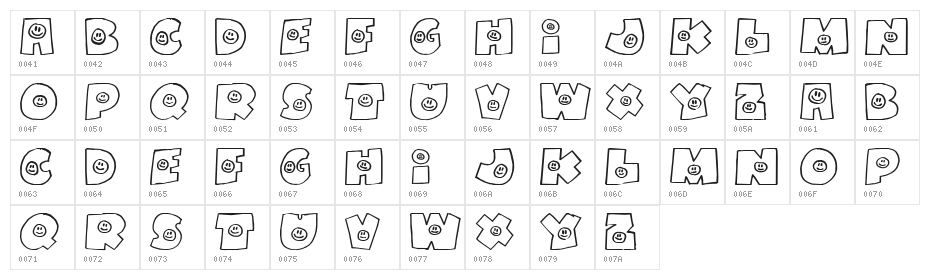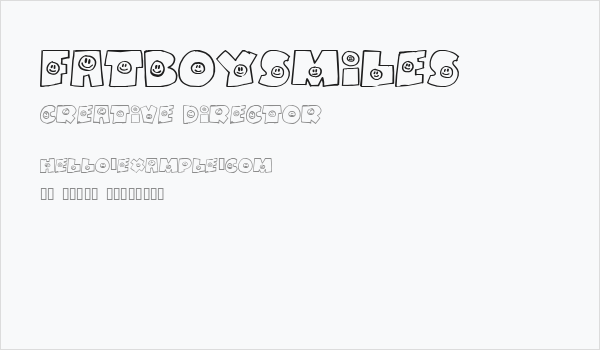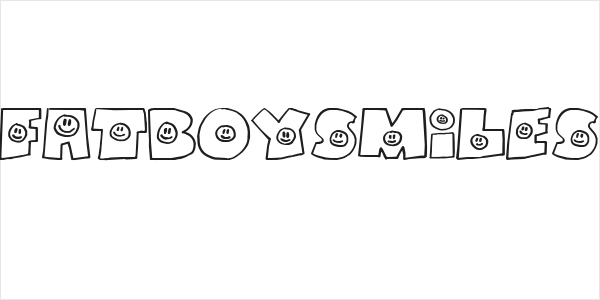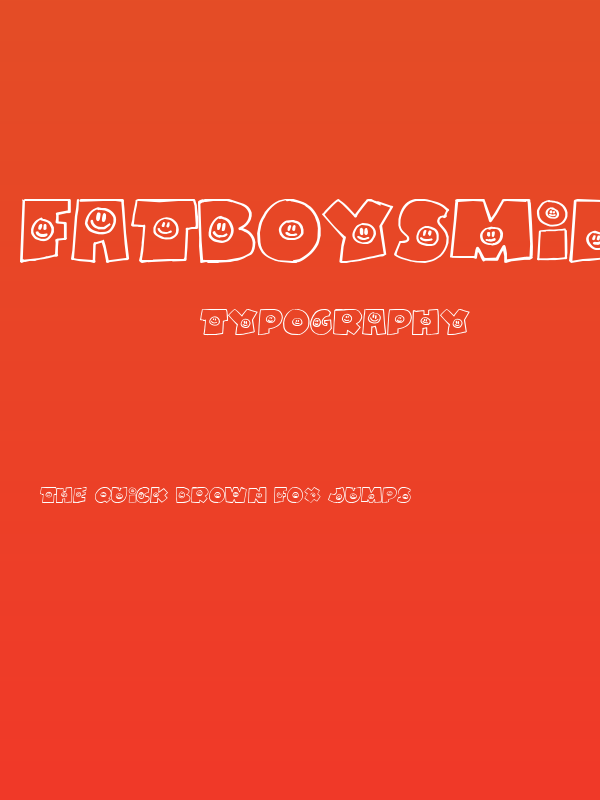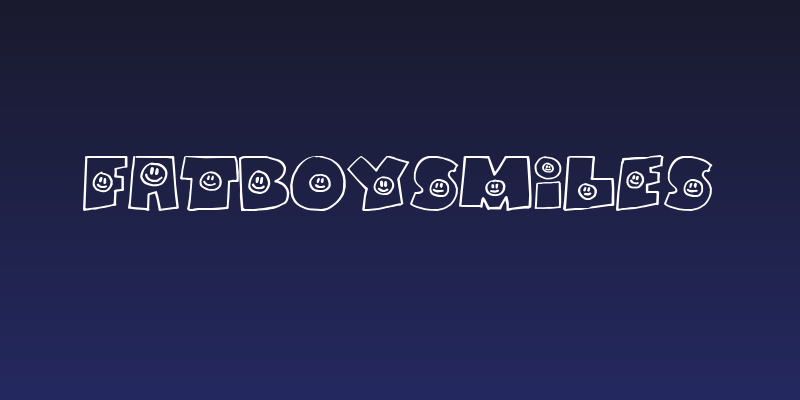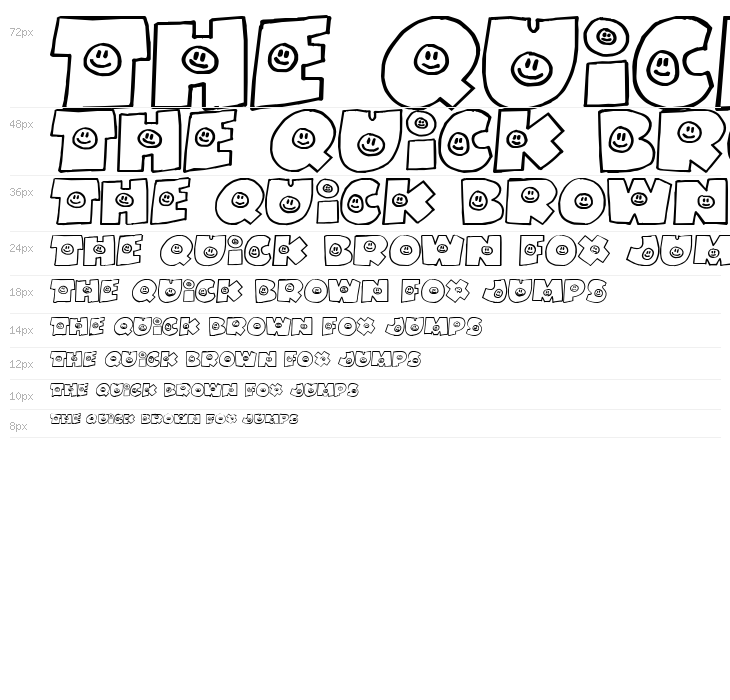
FatBoySmiles Font
✎ Outline
| Stile generale | Playful, Whimsical |
| Progetti proposti | Ideal for children's books, playful branding, party invitations, and any design requiring a joyful touch. |